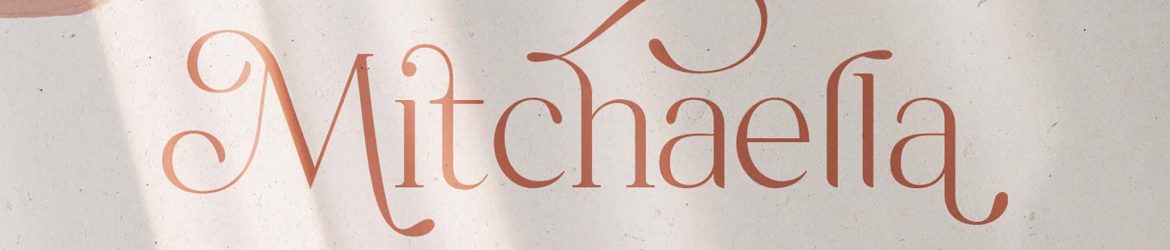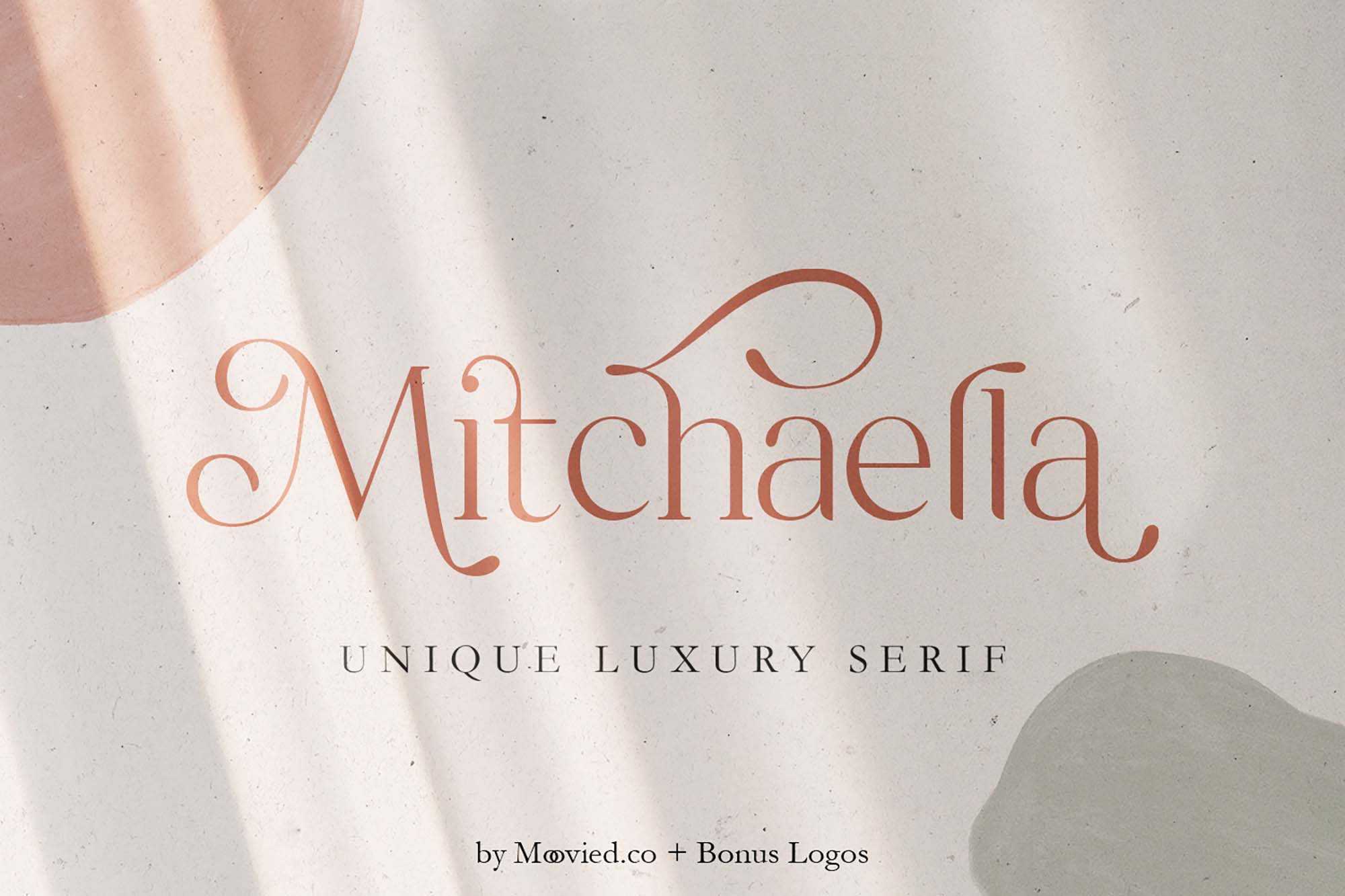
Mitchaella Luxury Serif Font
A fonte Mitchaella Luxury Serif é perfeitamente adaptada para criar uma convite de casamento, um recurso gráfico essencial para eventos especiais. Em um mundo onde as tradições dos casamentos podem variar significativamente entre países, o design de convites mantém sempre sua essência: a união de um casal celebrada pelos entes queridos. Quando se quer chamar a atenção de alguém especial para um evento tão ímpar, uma convite é o meio perfeito de anunciar a festa de casamento. Para os que ainda estão hesitantes sobre a estética do design do convite, apresentamos Mitchaella Luxury Serif, uma fonte que pode transformar a ideia de um convite do zero. A fonte Mitchaella Luxury Serif não apenas é elegante e profissional, mas também permite que você personalize a sua própria identidade visual para criar um convite que reflete seu estilo único e que faz justamente o papel do qual a ocasião necessita.